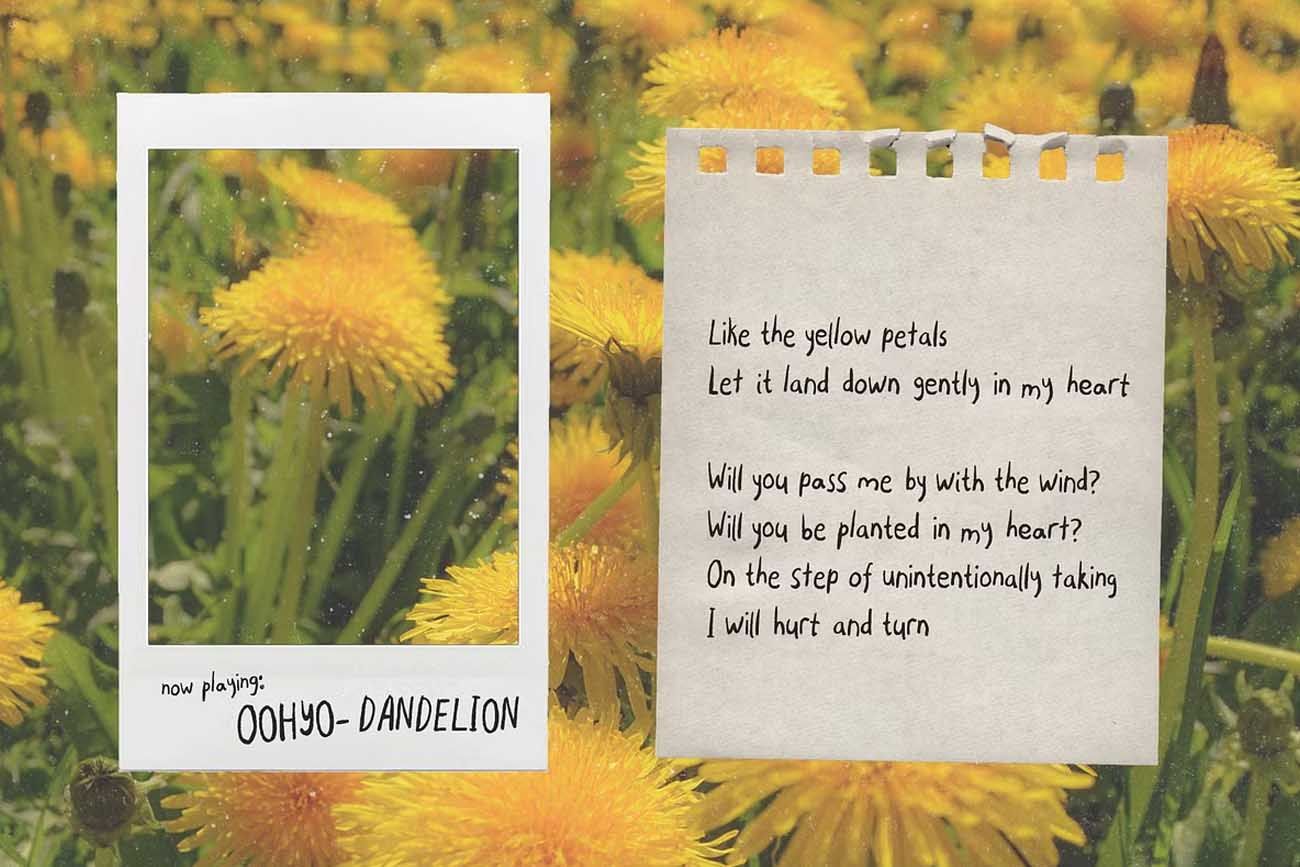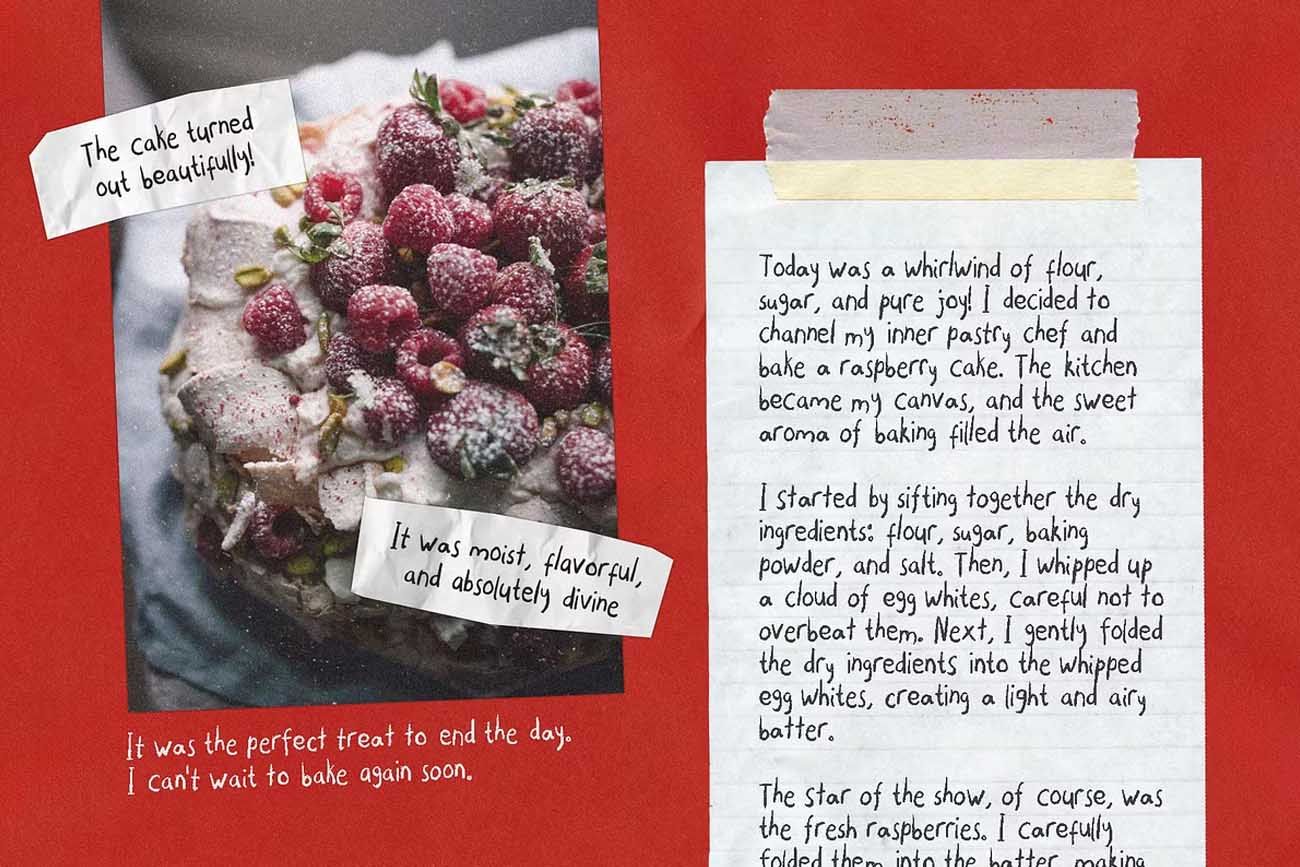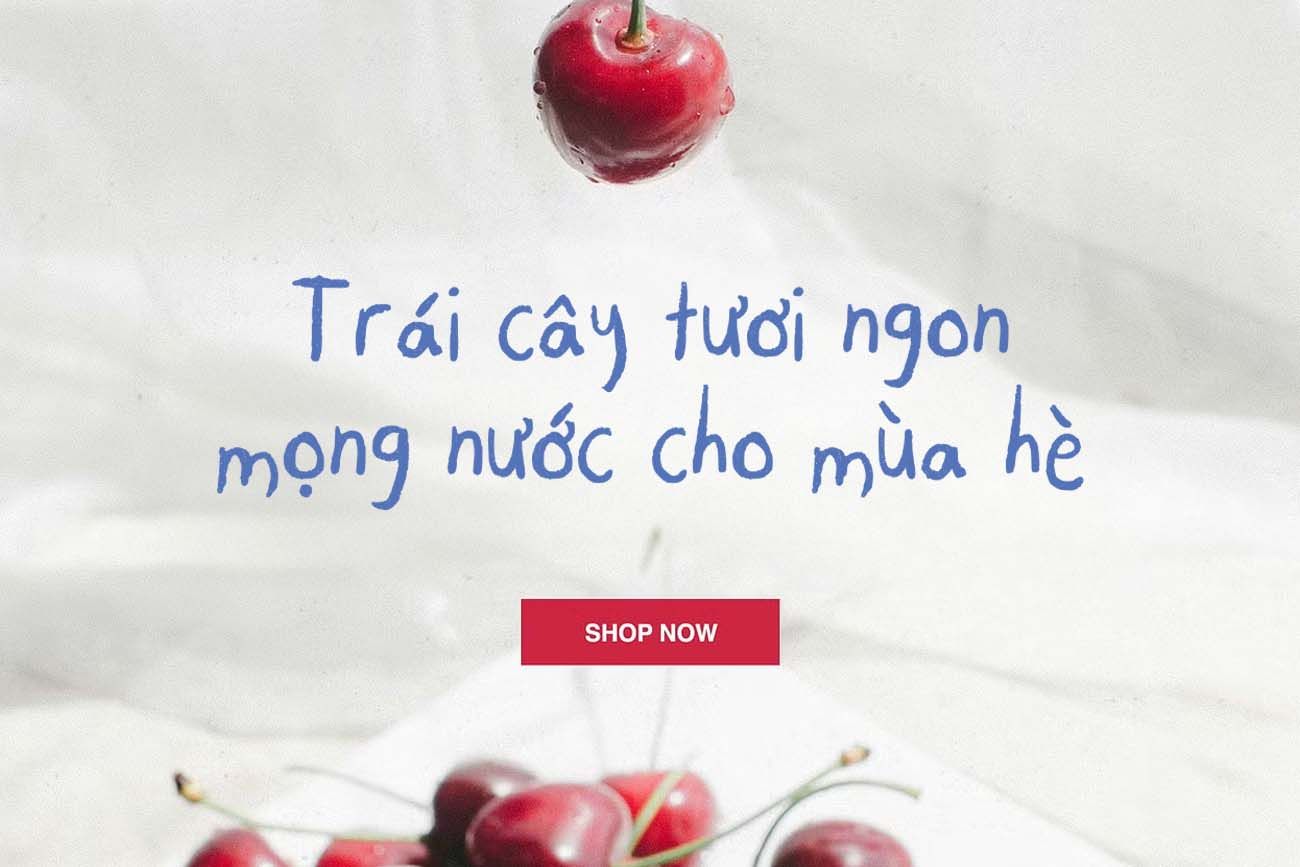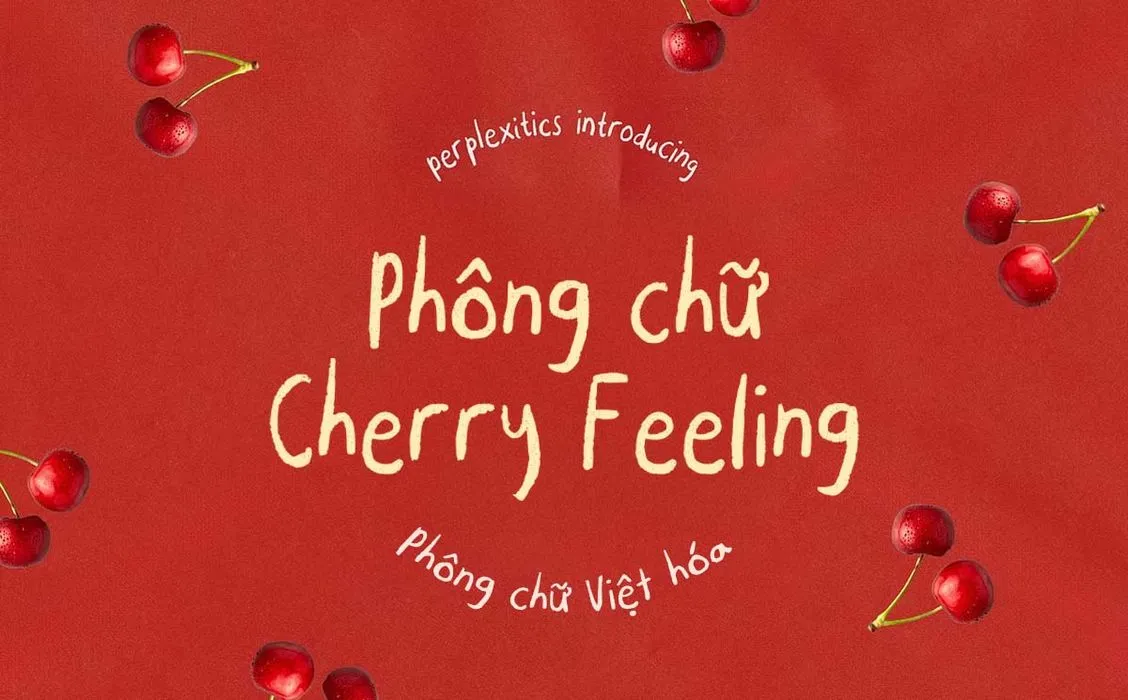
Bạn đang tìm kiếm một font chữ viết tay dễ thương để thổi hồn vào thiết kế của mình? Hãy khám phá ngay font chữ Cherry Feeling – một lựa chọn tuyệt vời dành cho những ai yêu thích sự ngộ nghĩnh, mềm mại và mang đậm chất thủ công. Font đã được Việt hóa hoàn chỉnh bởi Phạm Sơn, hỗ trợ đầy đủ tiếng Việt, đảm bảo tính thẩm mỹ và dễ dùng trong mọi dự án sáng tạo.
Font chữ Cherry Feeling là một kiểu phông chữ viết tay ngộ nghĩnh, mô phỏng nét chữ tay tự nhiên như được viết bằng bút chì hoặc cọ mềm. Các ký tự mang phong cách thô mộc, cao thấp không đều – tạo cảm giác gần gũi, tự do và không rập khuôn. Đây là dạng font chữ cute được ưa chuộng trong các thiết kế thiên về cảm xúc, cá nhân hóa hoặc sản phẩm dành cho trẻ em.
Font chữ Cherry Feeling sở hữu những đường nét mềm mại, hơi gãy nhẹ nhưng đầy cảm xúc, mô phỏng chân thực nét viết tay tự nhiên và ngẫu hứng. Chính sự “lệch chuẩn” có chủ đích ấy lại tạo nên vẻ đẹp nghệ thuật ngộ nghĩnh, đáng yêu.
Đặc biệt, font đã được Phạm Sơn (Fontdep.vn, S99.vn) Việt hóa cẩn thận, hỗ trợ đầy đủ tiếng Việt cùng hệ thống dấu thanh rõ ràng, đảm bảo tính ứng dụng cao trong mọi thiết kế.
Font chữ viết tay Việt hóa này cực kỳ linh hoạt trong thiết kế:
Thiệp cưới, thiệp cảm ơn, thư viết tay
Poster hoạt hình, sách thiếu nhi, bảng tên mầm non
Logo sản phẩm handmade, quà tặng cá nhân hóa
Bao bì sản phẩm cute: bánh kẹo, đồ chơi, đồ dùng học tập
Cherry Feeling không chỉ là một font chữ dễ thương về mặt thị giác, mà còn truyền tải sự tự nhiên và cảm xúc chân thành trong từng nét bút. Với phiên bản Việt hóa hoàn chỉnh bởi Phạm Sơn, bạn hoàn toàn có thể ứng dụng linh hoạt trong mọi dự án thiết kế cần sự gần gũi, sáng tạo và “có hồn”.(title, description, slug, tags) cho bài viết này không?